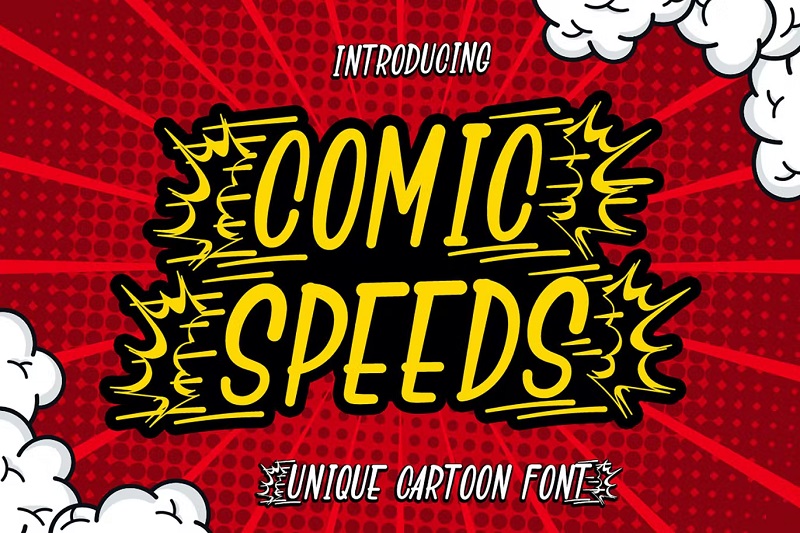
32 أفضل الخطوط المصورة للكوميك ستريبس والمانجا والرسوم المتحركة
نشرت: 2023-01-17هل تريد كتابة القصص المصورة الخاصة بك مثل المحترفين؟ ستحتاج إلى أفضل الخطوط المصورة للوظيفة - وأنت في المكان المناسب للعثور عليها.
لقد بحثنا في شبكة الإنترنت لاختيار أفضل الخطوط للكتب المصورة والمانجا والرسوم المتحركة حتى لا تضطر إلى ذلك.
ولا ، نحن لا نتحدث عن Comic Sans هنا - يوك.
نحن نتحدث عن أفضل الخطوط المصورة ، من قبل أفضل الفنانين والمصممين ، والتي تم استخدام العديد منها في جميع أنحاء العالم في المطبوعات المصورة والبرامج التلفزيونية الشهيرة.
مستعد؟ دعونا نتعمق في ذلك!
أفضل 32 خطًا هزليًا (مجاني ومدفوع)
1. Boom Comic Font - أفضل اختيار لدينا
Boom هو خط هزلي متفجر سميك للغاية ومثير. يقفز من الصفحة ويسهل قراءته بأي حجم. يأتي في تنسيقات OTF و TTF
لماذا هذا هو الاختيار الأفضل لدينا:
يحتوي Boom على كل ما نبحث عنه في خط الكتاب الهزلي. إنه صوت عالٍ ، في وجهك ، ومليء بالشخصية. Boom هو الخيار الأمثل لتلك الكلمات الصوتية المحكية التي تريد القفز عليها من الصفحة. انطلق! تنبيه! كابو!
2. كسر فكاهي
Breaking The Comic هو خط مرح يكسر جميع القواعد. إنه يتميز بنسيج فريد متشقق وأحرف جريئة وسميكة تقفز من الصفحة. وفقًا لاسمه ، يبدو الخط "مكسورًا" ، مع صور رمزية مصممة لتبدو وكأنها ممزقة إلى أجزاء. يأتي مع جميع الحروف الرسومية القياسية ومتوفر بتنسيقات OTF و TTF.
3. بادابوم
إذا كان هذا الخط يبدو مألوفًا ، فذلك لأنك ربما رأيته من قبل — على الأقل ، سيكون لديك إذا كنت من محبي الكتب المصورة.
Badaboom هو الخط الهزلي الأصلي الذي تم استخدامه في جميع أنحاء العالم في المطبوعات والتلفزيون. الأسلوب الخفيف والمثقل مبدعًا ، وهو خيار آمن لأي نوع. وأفضل جزء؟ إنه مجاني لمنشئي القصص المصورة المستقلين / الصغار!
4. مانجاكا
Mangaka عبارة عن خط رئيسي للرسوم المتحركة مثالي للمانغا ، والأشرطة الهزلية ، وكتب الأطفال ، والروايات المصورة ، والعديد من مشاريع التصميم الأخرى. يتضمن الحروف والأرقام وعلامات الترقيم.
5. ميستيريو
العمل على شريط كوميدي بوليسي؟ تحقق من Mysterio - خط هزلي كئيب مليء بالمكائد والغموض. يتميز هذا الخط الفضولي بضربات مموجة قليلاً ويمكن قراءته بشكل كبير. يتضمن جميع الحروف الرسومية الأكثر أهمية ، بما في ذلك اللاتينية AZ ، و az ، والأرقام ، وعلامات الترقيم.
6. نيكوبول
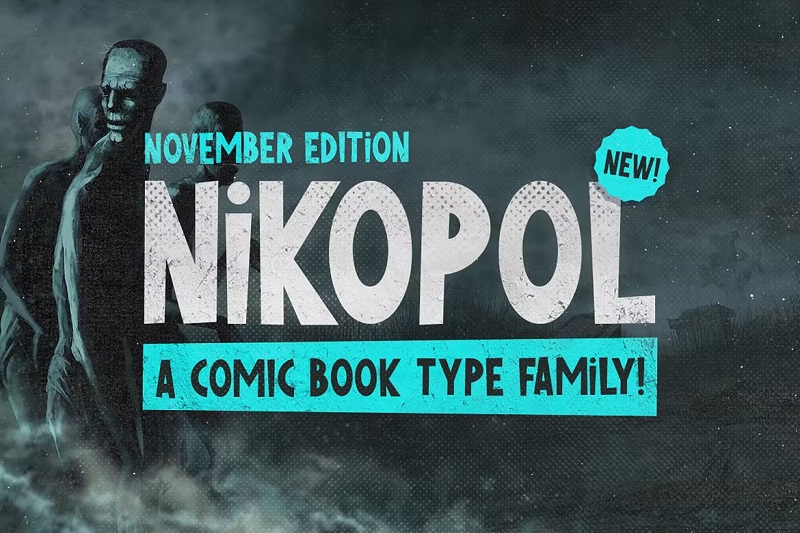
Nikopol هي عائلة خطوط غريبة ورائعة تحت عنوان الكتاب الهزلي. يأتي بثلاثة أنماط: عادي ، ونصف ، وخشن. نحب بشكل خاص إصدار الألوان النصفية. يحتوي على نسيج كتاب هزلي أصيل.
تتميز النسخة الخام بضربات متموجة تمنحها جمالية مخيفة. يمكنك مزج الأنماط المختلفة ومطابقتها وفقًا لطبيعة المشهد. إنه خط ذو أحرف استهلالية كاملة ، لذا لا يوجد إصدار كامل بأحرف صغيرة ، ولكن هناك بدائل بأحرف صغيرة "i" و "m".
7. مكتنزة
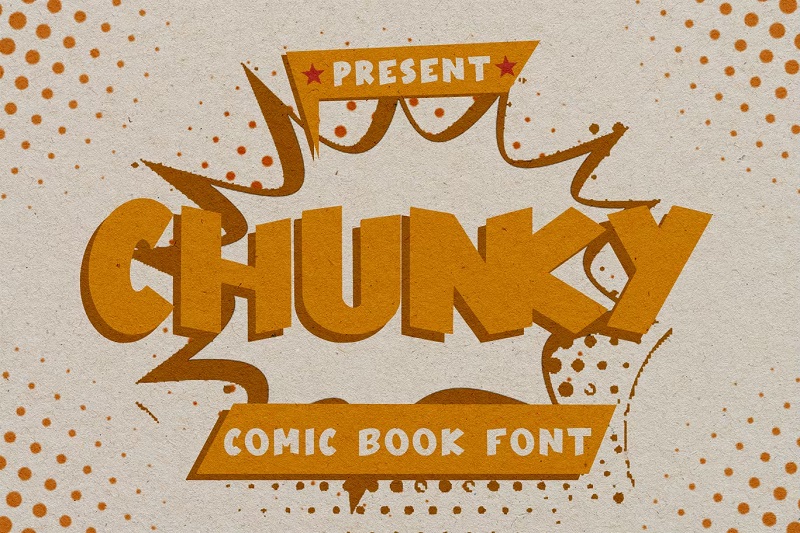
Chunky هو خط كتاب هزلي ممتع ومبهج يستحق المراجعة. يأتي بأحرف كبيرة وصغيرة ورموز وأحرف مركبة ، مع دعم متعدد اللغات.
8. محارب الجريمة
Crime Fighter هو خط رائع آخر مصمم بشكل متعمد لاستخدامه في الكتب المصورة. إنه يحاكي المعالجة التقليدية وهو متعدد الاستخدامات بما يكفي للعمل بشكل جيد في أي نوع من القصص المصورة ، ولكنه مناسب بشكل خاص لموضوعات الأبطال الخارقين.
9. ويب كوميك
Webcomic هو محرف هزلي مكتوب بخط اليد بواسطة المصمم Gasstype. تتميز أشكالها البسيطة بحروفها اليدوية المميزة ، وهي متعددة الاستخدامات للغاية.
10. كلاسيكاب
Klasikap هو خط عرض هزلي قوي يحزم لكمة. استخدمه للحوار الذي تريد القفز من الصفحة وجذب انتباه القارئ.
11. الكرة الأبله
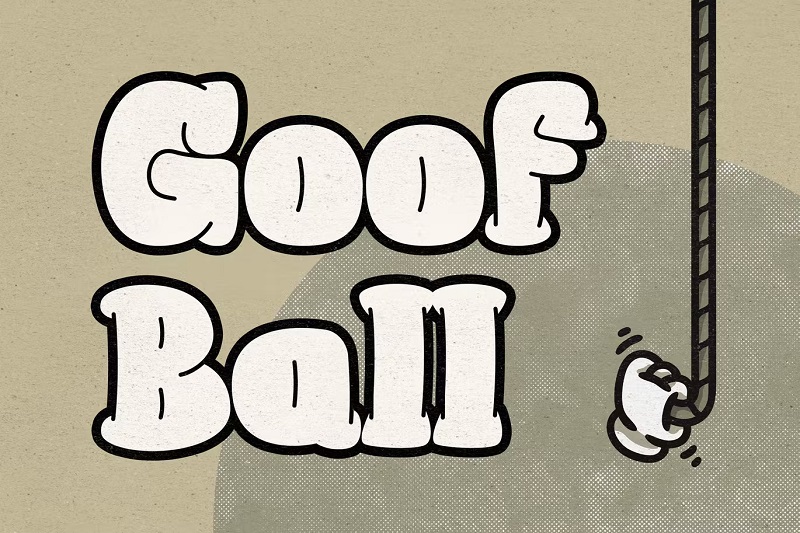
Goof Ball عبارة عن خط رسوم متحركة حسي به ضربات كبيرة وعدادات مضغوطة. هناك شيء مضحك لا يمكن إنكاره حوله ، وهو يتمتع بهذا الأسلوب الرجعي الذي يجعله مثاليًا للرسوم المتحركة في المدرسة القديمة والكوميديا الفكاهية.
12. بليزاريوس
Belizarius هو الخط المثالي للكاريكاتير الرعب. إنه ذو طابع غريب ويبدو أنه قد تم خربشته أو خدشه في الصفحة. تم إنشاؤه من قبل كاتب الكتاب الهزلي الحائز على جائزة Nake Piekos ، وهو مجاني تمامًا لمنشئي القصص المصورة المستقلين!
13. فونيكورن
Funicorn هو خط كرتوني لطيف مثالي للرسوم الهزلية والمانجا ، بالإضافة إلى تغليف منتجات الأطفال ، وأغلفة الكتب ، والملصقات ، والكثير من المشاريع الأخرى.
14. سوريتون كاريكاتير
Sureton Comics هو محرف مرسوم باليد بواسطة Adil Budianto. إنه محطّم وإنساني ، بمظهر بسيط ونظيف ومتعدد الاستخدامات بشكل جيد بما يكفي للعمل في العديد من التصميمات المختلفة.
15. تسوكي
Tsuki هو محرف جميل مستوحى من اليابان وهو مثالي للرسوم المتحركة المانجا وغيرها من التصميمات ذات الطابع الآسيوي.
16. بونكون
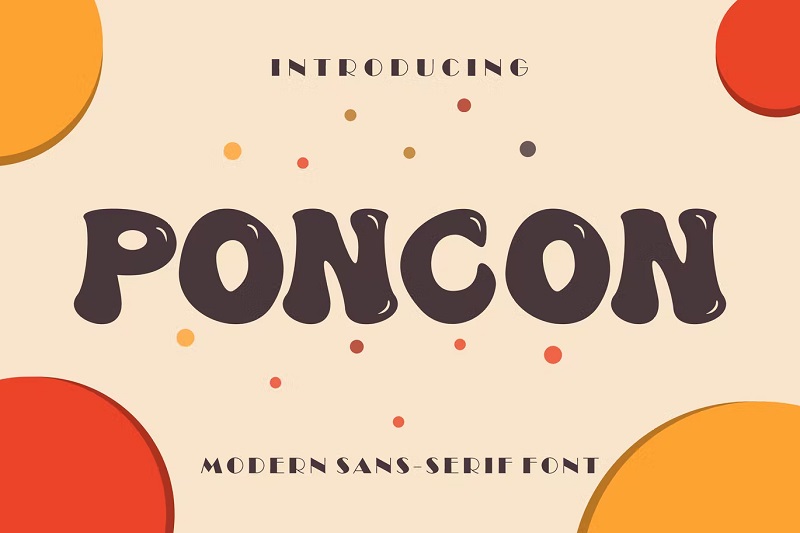
Poncon هو خط sans serif حديث بزوايا دائرية وأسلوب مرح. إنه خيار جيد آخر للمانغا والكوميديا المرحة.
17. أفضل الأصدقاء
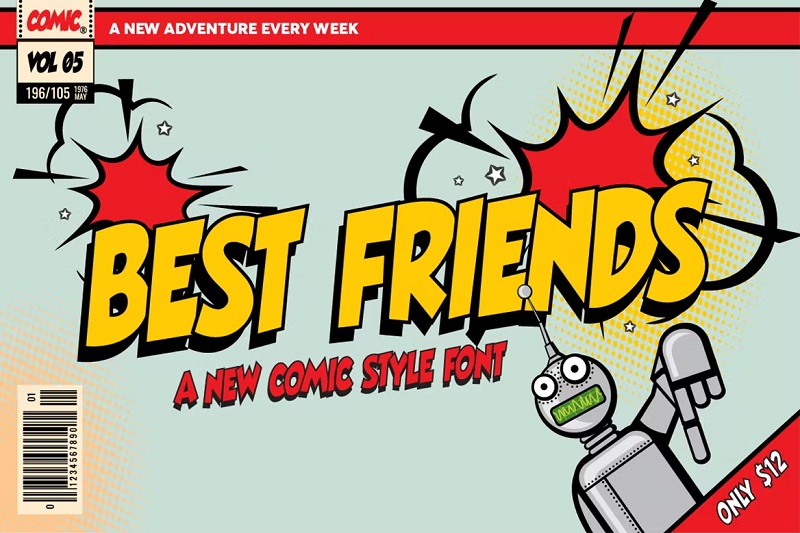
Best Friends هو خط على غرار الكتاب الهزلي بواسطة Salt and Pepper Designs. إنها مليئة بالشخصية ومؤثرة للغاية.
18. الخمرة
Vintagity هو خط عرض هزلي بنسيج باهت رقيق يمنحه مظهرًا قديمًا. يتضمن أحرفًا صغيرة وكبيرة وأحرفًا متعددة اللغات وأرقامًا وعلامات ترقيم.
19. ميسي بجرأة
Boldly Missy هو خط للكتابة اليدوية على الويب تم استخدامه كمربع حوار في "التعليمات الأساسية" الكوميدية الشهيرة على الويب. تم تصنيعه في عام 2006 من قبل المصمم الموهوب ميسي ماير وتم ترتيبه منذ ذلك الحين. إنها ليست مثالية ، لكنها قريبة جدًا - وهي مجانية!
20. الهزلي الصاحب
Comic Sidekick هي عائلة خطوط فرشاة فريدة مرسومة يدويًا تأتي في 11 نمطًا مختلفًا. هناك إصدار منتظم ، إصدار مخطط تفصيلي ، نمط مضمن ، إصدار بديل ؛ والمتغيرات المرسومة باليد والفرشاة والألم.
لا ينبغي أن تكتفي كتابتك بأعلى مستوى من الفن فحسب - بل يجب أن تكملها. حاول اختيار خط يتناسب مع فنك بشكل جيد. فكر في أشياء مثل الوزن والانحناء عند مقارنة خياراتك.
فكر في المقروئية
لا يبدو خط الكتاب الهزلي الجيد رائعًا فحسب - بل يجب أن يكون مقروءًا للغاية أيضًا. بعد كل شيء ، لا يزال الجزء الأكثر أهمية في الكوميديا هو القصة نفسها ، ولن تكون قادرًا على إخبارها إذا لم يستطع القارئ فهم الحروف الموجودة على الصفحة.
عندما تقارن الخطوط الهزلية ، تذكر أن الخط الذي يمكن قراءته بسهولة بأحجام كبيرة لن يكون من السهل قراءته بالضرورة عندما يتم تقليصه ليلائم صفحة الشريط الهزلي.